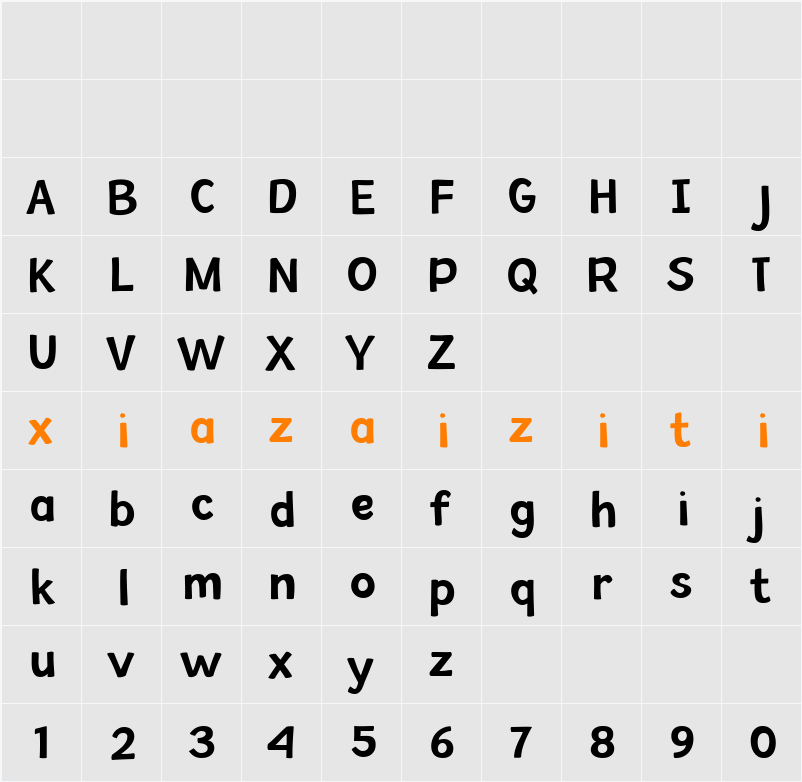
Winter Storm
Winter Storm,这款字体结构工整、笔画清晰,兼顾美观与易读性,适用于标题、正文、海报、包装、LOGO 等多种场景。字形优雅稳定,风格百搭耐看,适配日常排版与创意设计,让文字呈现更舒适、更具质感。Winter Storm一笔一画,皆是细节,以均衡的比例、流畅的线条打造舒适视觉体验,字形端正大气,风格简约现代。无论是商业设计、品牌宣传还是日常排版,都能轻松驾驭,让文字更有格调与力量。Winter Storm字体下载。